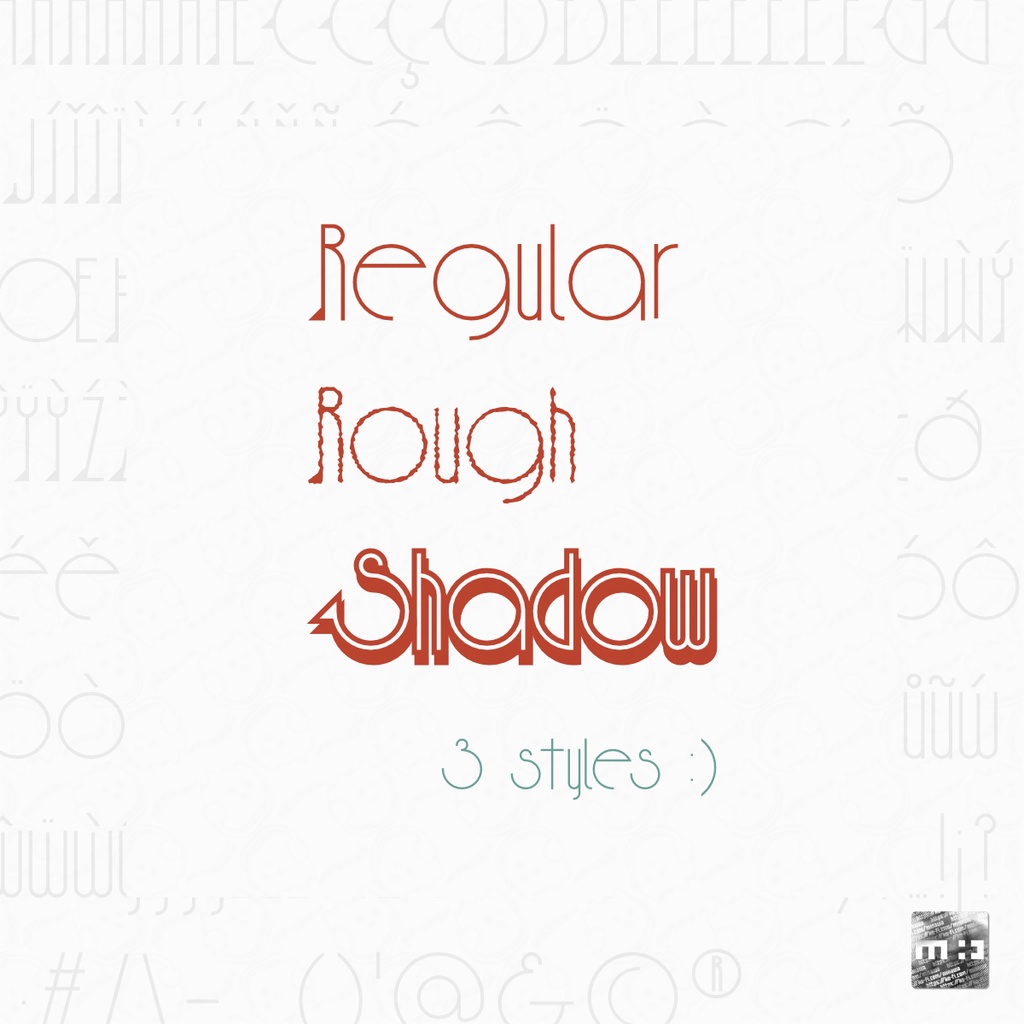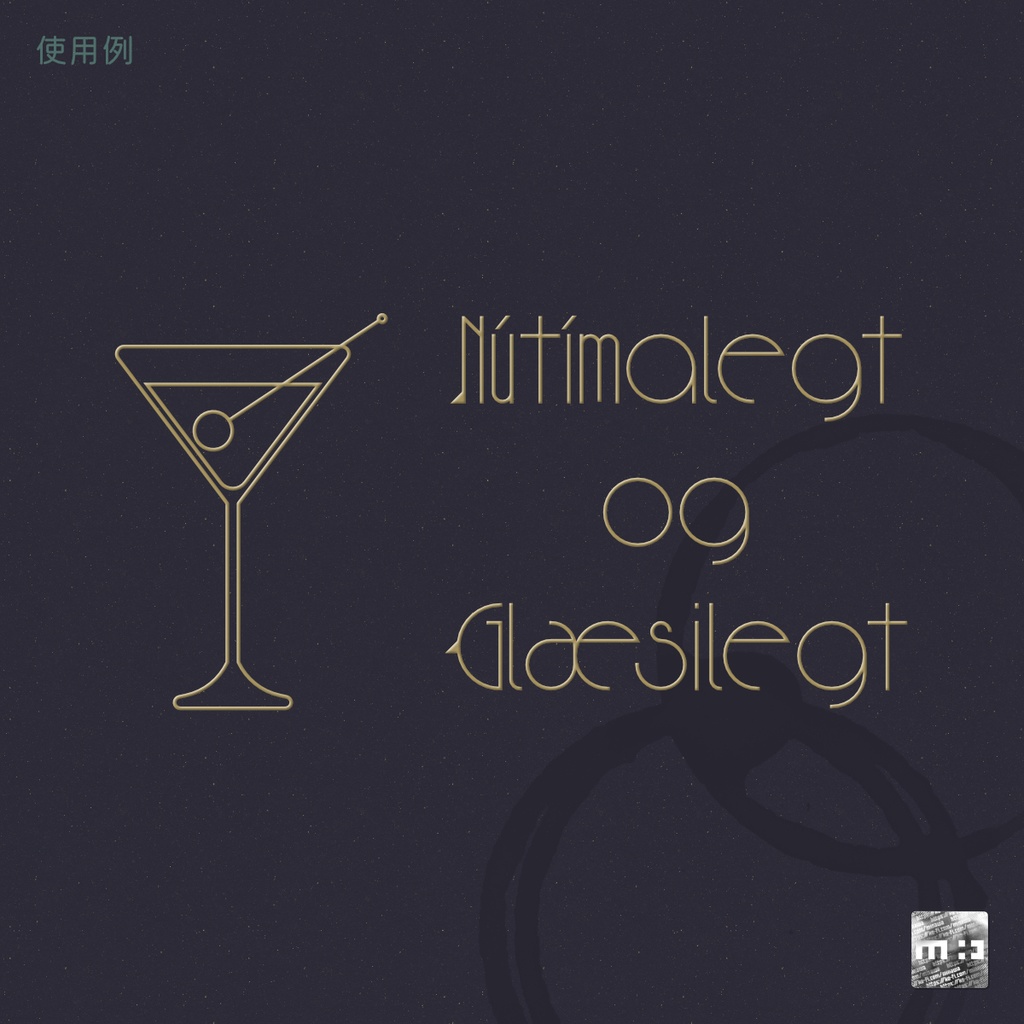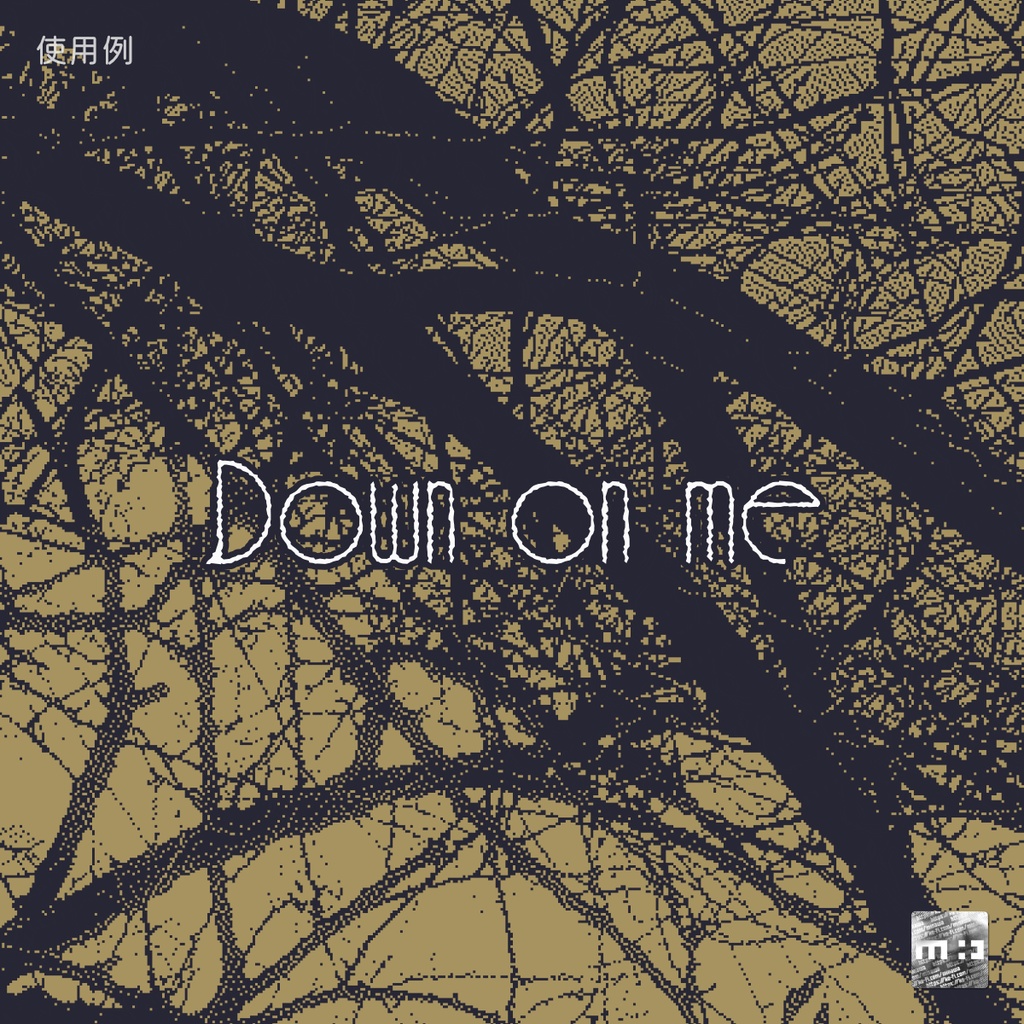
ピンヒールデコ フォント
収録文字
ABCDEFGHIJKLMNOPQRSTUVWXYZ abcdefghijklmnopqrstuvwxyz ÁÂÄÀÅÃÆĆČÇĊĎÐÉĚÊËĖÈẼǦĠIJÍǏÎÏÌJ́ĹŃŇÑÓÔÖÒØÕŒÞŔŘŚŠẞŤŢÚÛÜÙŮŨẂŴẄẀÝŶŸỲŹŽŻ áâäàåãæćčçċðéěêëėèẽǧġíǐîïìijj́ĺńňñóôöòøõœþŕřśšßţúûüùůũẃŵẅẁýŷÿỳźžż 0123456789 .,:;…!¡?¿·#/\-_()'@&©®